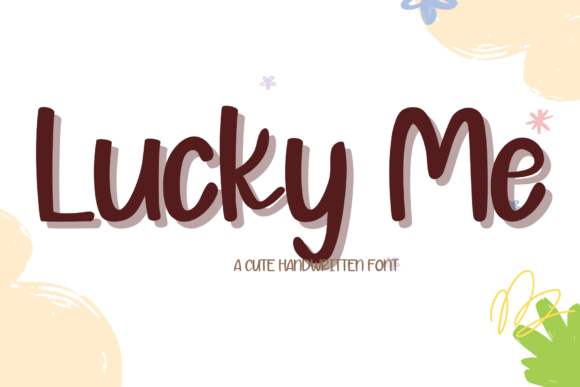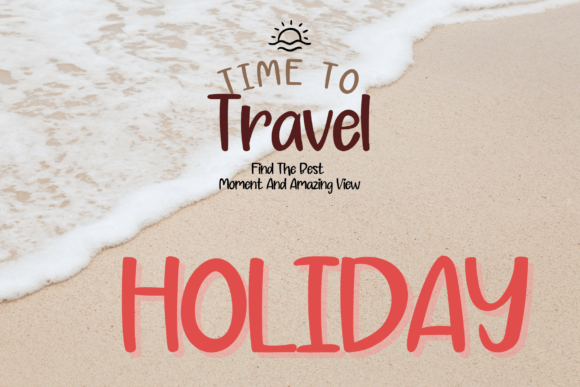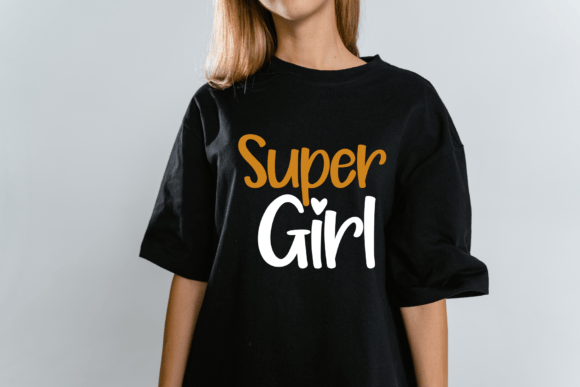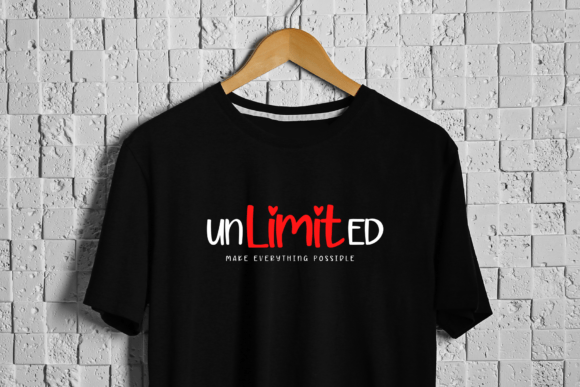
| ⭐ مجموعه فونت | دانلود فونت انگلیسی خوش به حالم Font Lucky Me |
| ⭐ توضیحات | Lucky Me یک فونت دستنویس دوستانه است که به هر یک از پروژههای طراحی، لوگوها، طرحهای عروسی، پستهای رسانههای اجتماعی، تبلیغات، بستهبندی محصول، طرحهای محصول، برچسب، عکاسی، واترمارک، دعوتنامه، لوازم التحریر و هر چیز دیگری ظرافت و کلاس میبخشد. پروژه ها. |